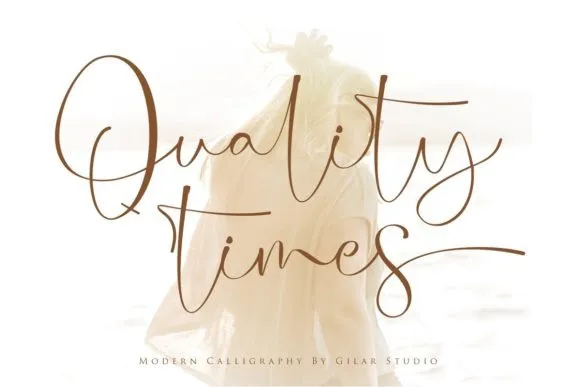
Quality Times Font – Download Grátis
A fonte ‘Quality Times Font’ é uma elegante tipografia script criada por Gilar Studio com um toque suave e natural. Suas linhas flutuantes proporcionam um visual único, que transmite sofisticação ao mesmo tempo que mantém o encanto casual. Esta font é perfeita para diversos usos, como logotipos, convites de casamento, títulos, adesivos para camisetas, assinaturas em cartão, sinalização, rótulos, notícias, outdoors e até mesmo selinhos. Seja você designer gráfico ou hobbyista, esta font é uma excelente opção para dar um toque distintivo a seus trabalhos.